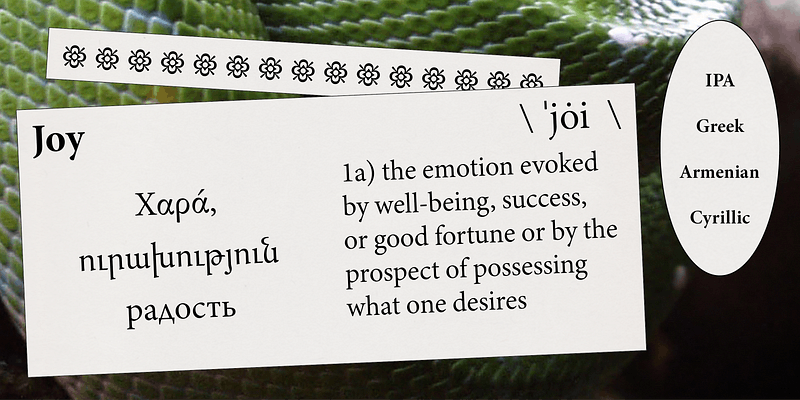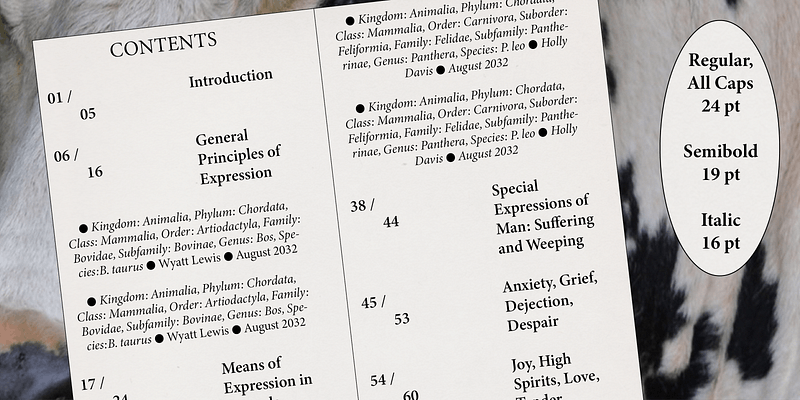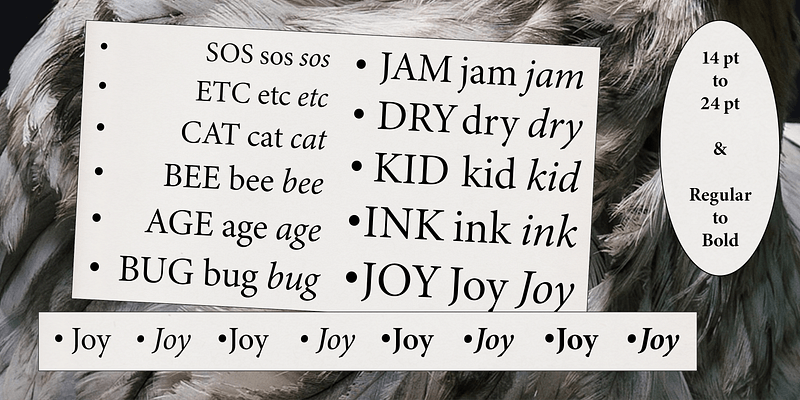
Minion은 Robert Slimbach가 제작하고 Adobe Originals](/foundries/adobe)에서 출시한 현대식 서체 제품군입니다. 최초 출시되는 날부터 Minion은 가독성과 우아함을 자랑하면서 도서 및 편집 디자인 등 다양한 텍스트와 디스플레이 분야에서 다재다능한 서체로서 입지를 굳히고 있습니다.
아프리카 언어와 베트남어 그리고 IPA(국제 음성 문자)에 적용되는 Latin 글리프 수가 두 배로 증가하면서 Slimbach는 Minion 3을 통해 Minion 제품군을 다시 검토하고 확장할 기회를 엿보고 있습니다. 또한 Slimbach에는 아르메니아 스크립트 외에도 상당히 세련된 키릴 및 그리스 스크립트가 있습니다.
Minion 3은 4가지 두께와 4가지 광학 크기(Display, Caption, Subhead, and text)로 제공됩니다. 각 두께와 크기에 일치하는 이탤릭체가 있습니다. 디자인 역사 둘러보기와 최신 확장된 Adobe 전용 서체 제품군의 기술적 사양에 대한 자세한 내용은 minion.typekit.com을 방문하십시오.
Adobe Originals 프로그램은 1989년 Adobe 사내 서체 파운드리로 시작하여 모범적인 디자인 품질, 기술적 충실도 그리고 미적 영속성을 가진 오리지널 서체를 창안하기 위해서 구성되었습니다.
현재 Type 팀의 임무는 디자인과 기술의 가능성을 모색하는 정교하고 심지어 실험적일 수도 있는 서체를 만드는 것입니다. Adobe Originals로 출시된 서체는 수년간의 작업 및 연구의 결과로서 그 개발의 야심과 품질이라는 점에서 업계의 표준으로 인정되고 있습니다.